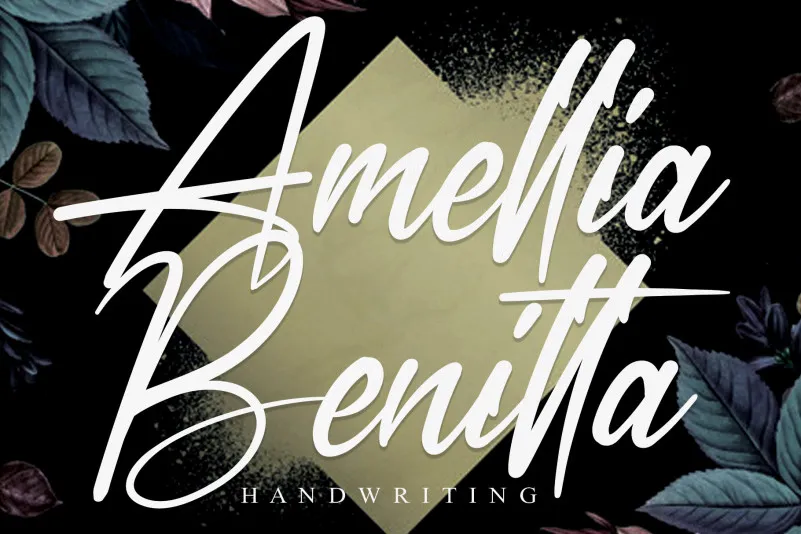
Amellia Benitta Script Font – Download Grátis
A fonte ‘Amellia Benitta Script Font’ é perfeita para quem valoriza um estilo autêntico e envolvente. Escreva mensagens pessoais com a delicadeza do script, ou adorne layouts com um toque de naturalidade. Esta elegante fonte hand-drawn foi criada pelo designer creativletter e oferece uma experiência única para aqueles que buscam algo diferenciado em suas criações digitais. Seja você quem escolhe o tamanho e a intensidade da letra, sua ‘Amellia Benitta Script Font’ proporcionará um toque autêntico e singular ao seu trabalho. Experimente essa fonte hoje e inspire-se com uma linguagem visual única e envolvente.